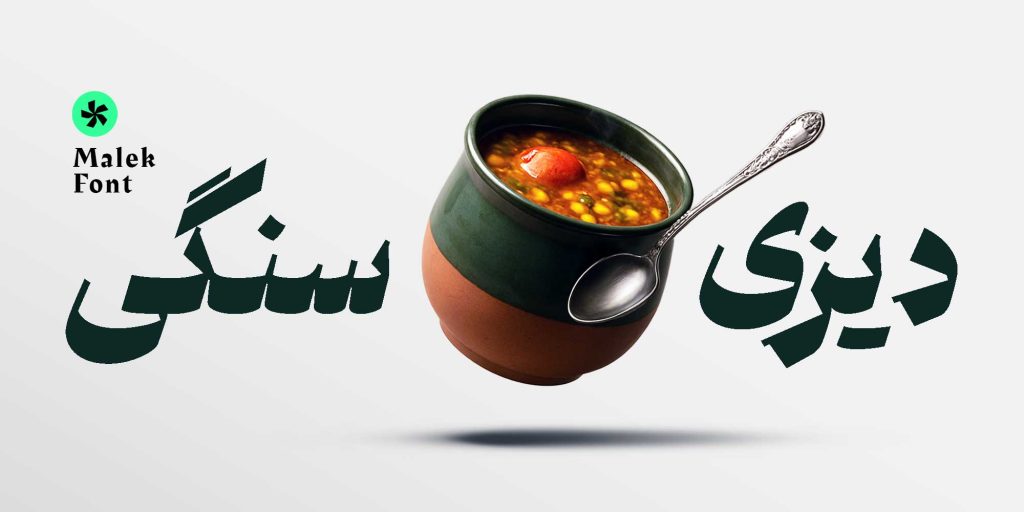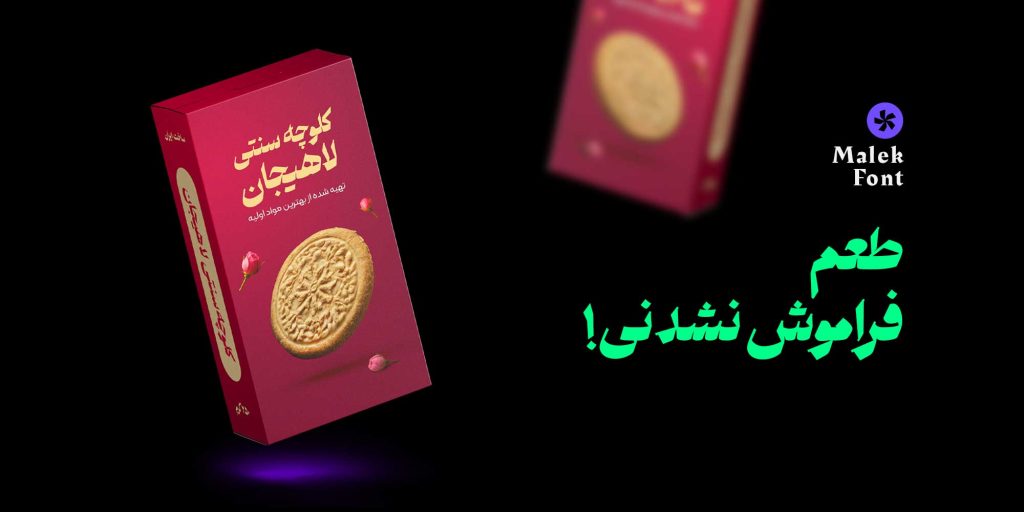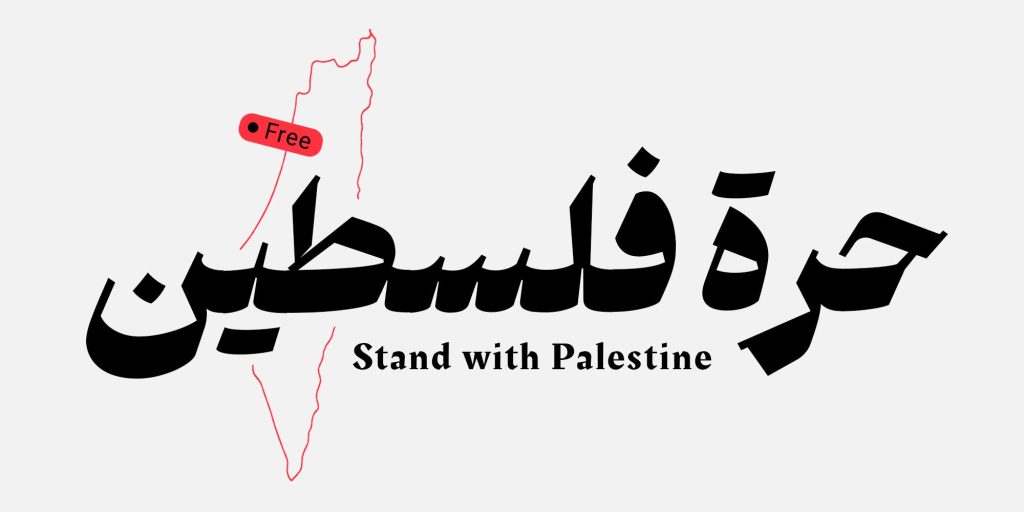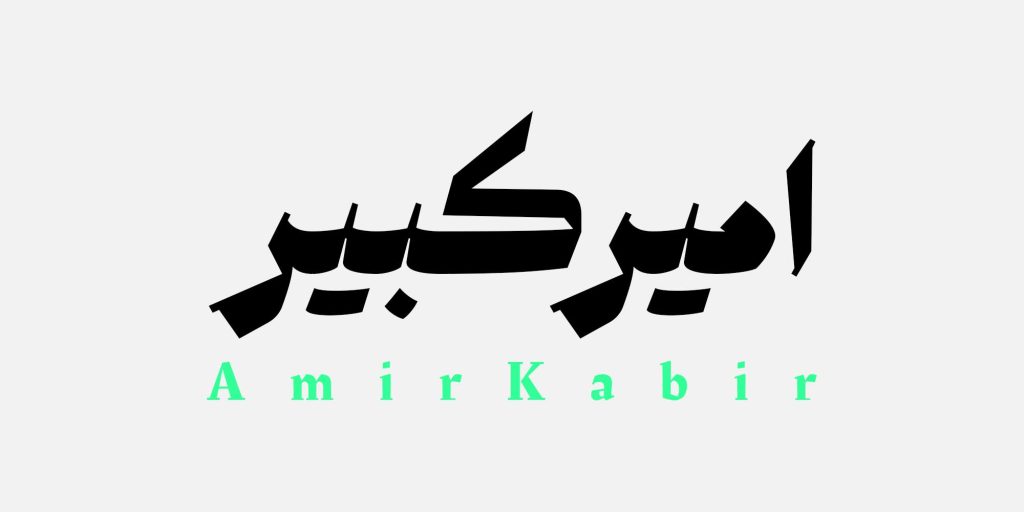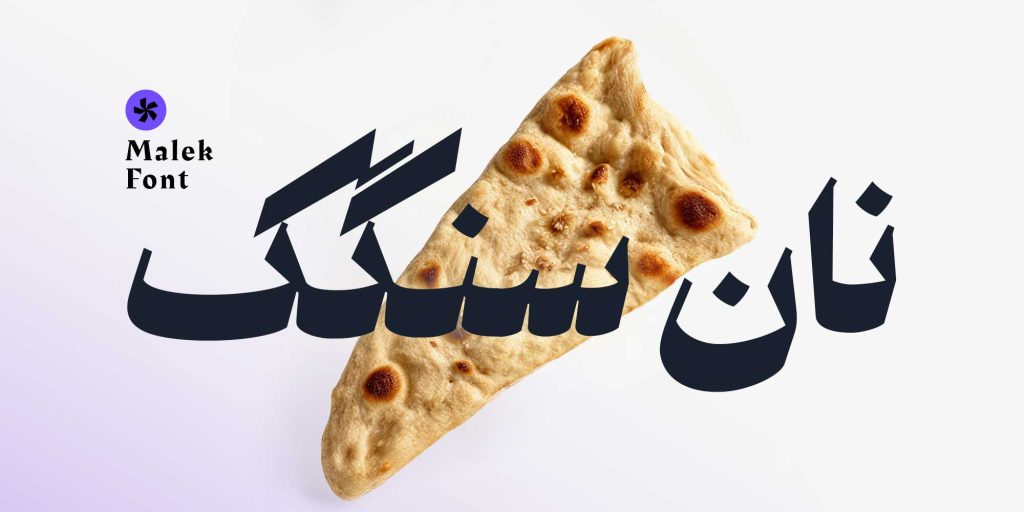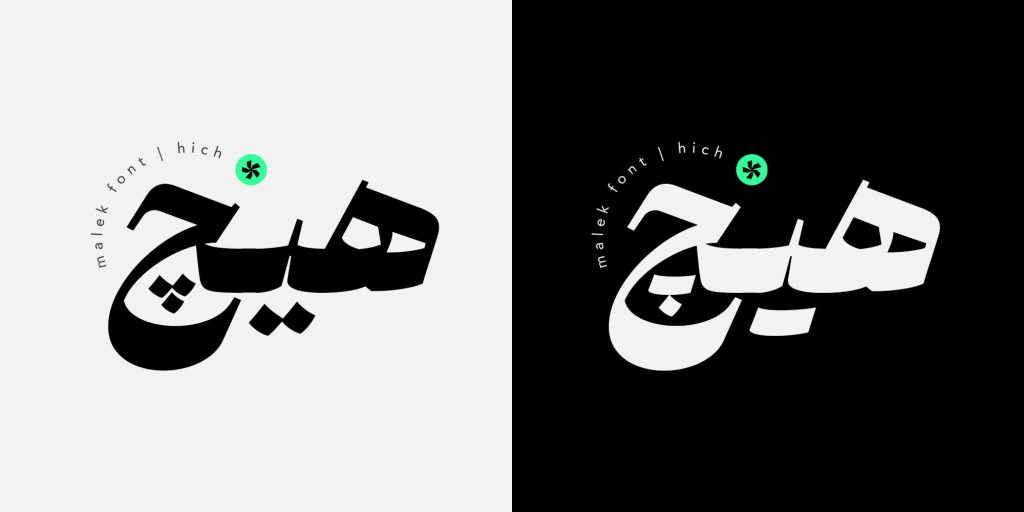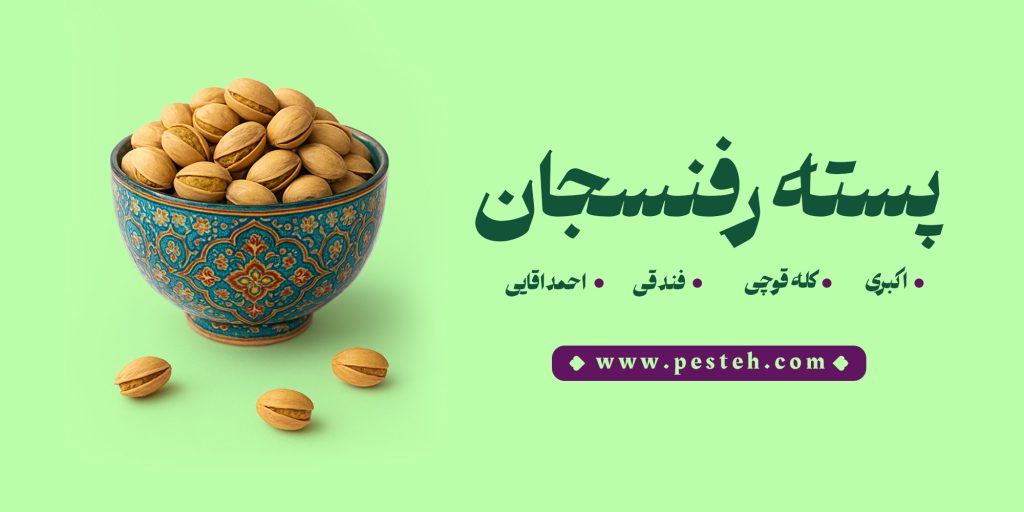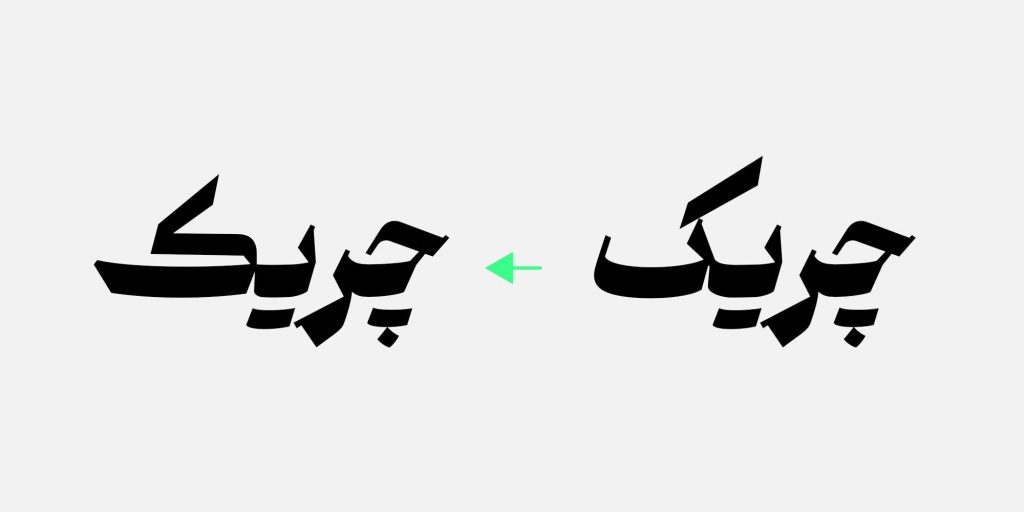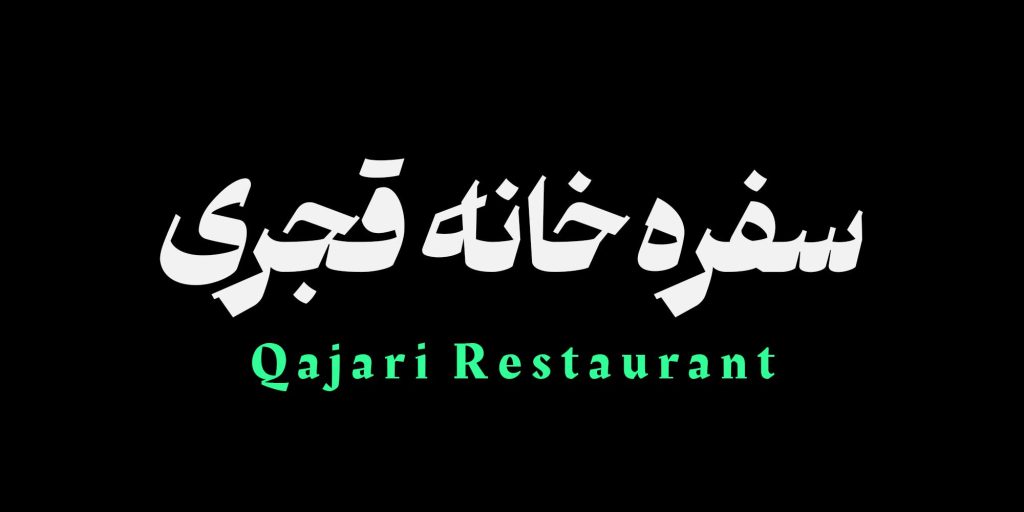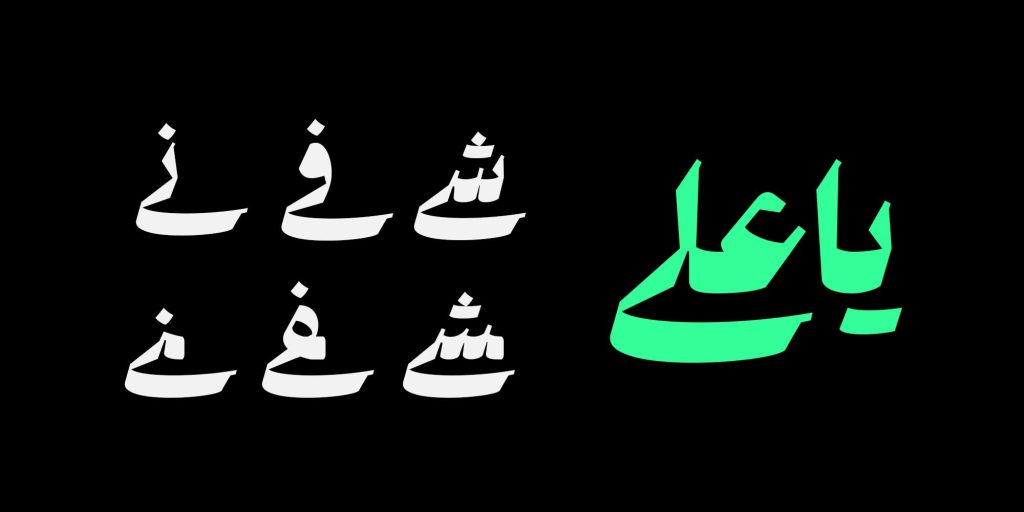
فونت ملک – آمیخته ای از هنر خوشنویسی
فونت ملک با هدف پیوند دادن اصالت خوشنویسی ایرانی با نیازهای گرافیک معاصر طراحی شده است.
ایده و روند طراحی این فونت در دورهٔ تایپتراپی مسلم ابراهیمی شکل گرفت و در همان دوره تکمیل شد.
ساختار ملک حاصل تلفیق نظم هندسی خط نسخ با لطافت و سیالی نستعلیق است؛ ترکیبی که تلاشی آگاهانه برای ایجاد تعادل میان سنت و مدرنیته بهشمار میآید.
فرمهای منحنی در کنار شکستهای زاویهدار، به این فونت شخصیتی اصیل، پویا و معاصر بخشیدهاند.
ملک انتخابی مناسب برای عناوین، تیتر پوسترها، جلد کتاب و پروژههای هویت بصری با حالوهوای ایرانی است.
این فونت در عین سادگی، جلوهای از شکوه و وقار خوشنویسی ایرانی را در قالبی نو بازتاب میدهد و تلاشی است برای بازآفرینی زیبایی کهن در زبان بصری امروز.
پشتیبانی قلم ملک از زبان های مختلف
تایپ فیس ملک از زبان های بسیاری پشتیبانی می کند از جمله این زبان ها می توان به زبان های فارسی عربی،انگلیسی و … اشاره نمود این تنوع از پشتیبانی گزینهای بیهمتا برای طراحان خوشذوق تایپوگرافی فارسی است تا توانمندی های خود را در قالب این قلم به تصویر کشند.
فارسی، تورکی، عربی، اردو، کوردی و جاوی